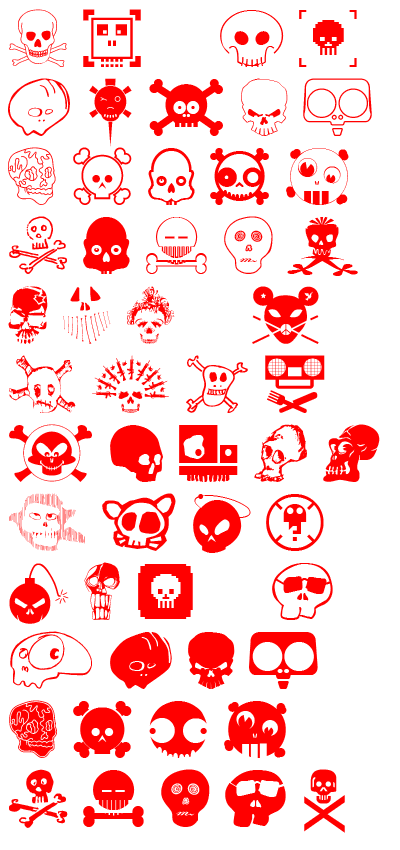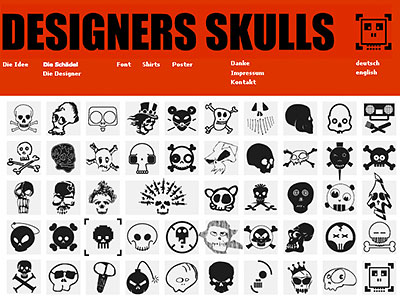
Kostenloser Totenkopf-FontFür Eckehard Beck ist der Totenkopf nicht nur ein Symbol des
Verfalls, sondern er steht auch für die Kennzeichnung rebellischer Ideen.
Und so kam ihm die Idee, einige Designerinnen und Designer um Beiträge
für eine Totenkopfsammlung zu bitten. Daraus ist ein Font entstanden, der
als kostenloser Download bereit liegt. Gerade rechtzeitig zu Halloween ... und
![]() ![]() Für die Aktion haben Ekkehard Beck und Lutz Härer die Webseite Designers Skulls eingerichtet, die alle Schädel und deren Schöpfer einzeln vorstellt. Dazu gibt es ein T-Shirt, Poster und Ansichtskarten. Auch der offizielle DIN-Totenkopf ist im kostenlosen Font enthalten (mit freundlicher Genehmigung des Deutschen Institutes für Normung e. V.): ![]() Die Totenkopf-Schrift für Mac oder PC ist über Fontkitchen downloadbar, hier die direkten Links: Designers Skulls Mac ... Designers Sculls Windows ... ![]() Abbildung: Fontkitchen Herausgegeben: Do - Oktober 27, 2005 at 10:30 vorm. | |